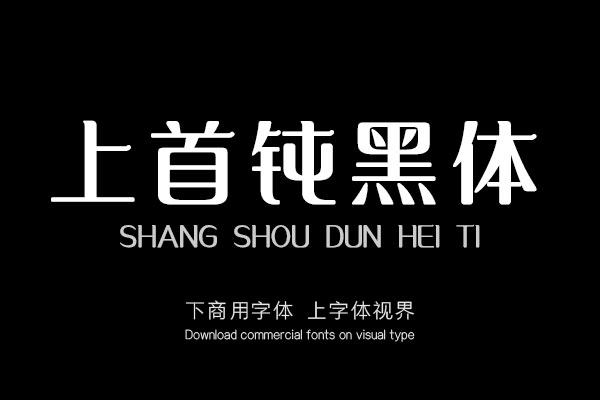
上首钝黑体,字体风格干净利落,方正庄重,整体少了锐利的尖角,使字体显得更为亲和。购买须知:“下载服务费”与“字体VIP”所获得字体 仅用于个人非商用, 商用请联系付费授权。本字体为电脑用字,手机没有root权限不支持直接手机换字(手机如何root,请自行百度搜索教程)。购买前请先 了解清楚后再付款 ,字体为虚拟产品无法回收 一旦购买不支持退款。